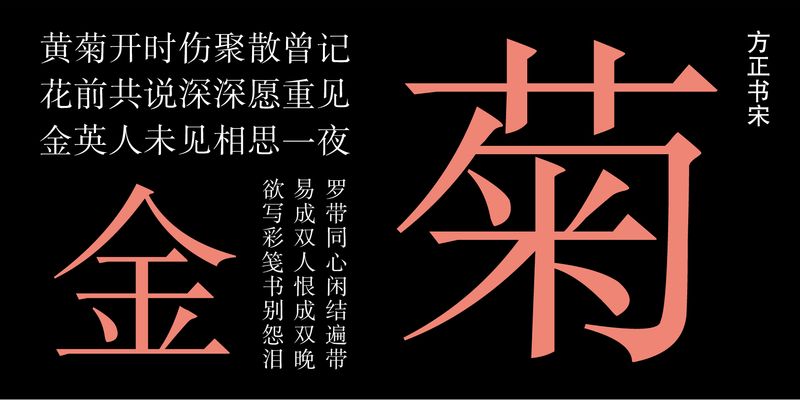
Fāng Zhèng Shū Sòng basiert auf der Schrift SongEr des Shanghai Institute of Printing Technology. Das ursprüngliche Design, das fast 60 Jahre alt ist, war für den am häufigsten verwendeten kleinformatigen Textsatz gedacht. Der Stil der Fāng Zhèng Shū Sòng ist geradlinig und schön, mit einem moderaten ZhongGong (ähnlich wie Counter) Design, was sie zu einer sehr klassischen Schrift macht. Die Fāng Zhèng Shū Sòng ist aufgrund ihrer Lesbarkeit, visuellen Ermüdungsresistenz und drucktechnischen Anpassungsfähigkeit eine beliebte Wahl für lange Texte in Zeitschriften und Büchern.